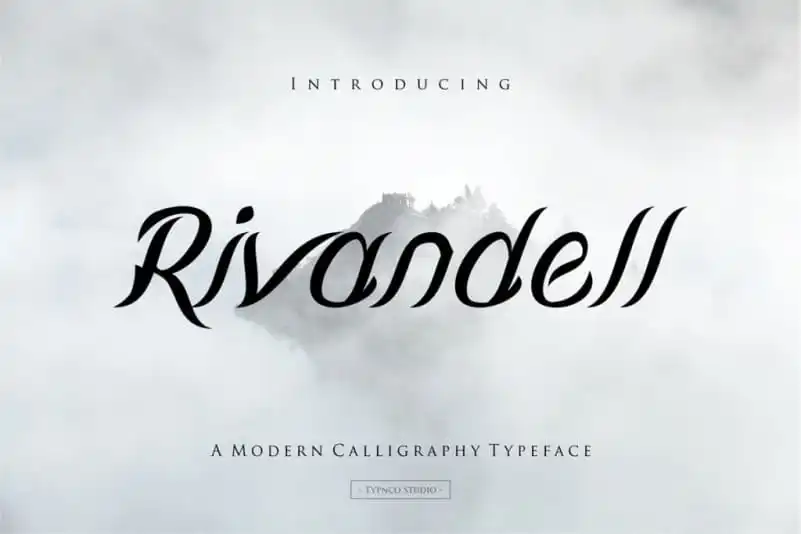
A Rivandell Script é uma nova fonte feita à mão com estilo calligrafico que se destaca no mercado das letras digitais. Esta fonte perfeita para postais de casamento traz um toque moderno às antigas grifes reais e ficcionais, mantendo-se fiel ao seu aspecto elegante e sofisticado. Rivandell é uma tipografia cursiva ideal para diversos projetos, desde convites de casamento até capas de livros ou pequenos ditames. A fonte foi criada por Typnco Studio e oferece um look autêntico e impecável que se destaca em ambos os ambientes impressos e digitais. Suas linhas fluidas e detalhes meticulosamente cuidados fazem da Rivandell Script uma escolha perfeita para quem deseja criar designs com uma forte presença visual, capazes de expressar elegância e elegância ao mesmo tempo. Composta por um conjunto de caracteres que inclui acentos diacríticos e simbolos, a fonte é versátil o suficiente para adaptar-se em diferentes formatos e aplicativos. Caso seja seu objetivo apresentar uma mensagem elegante e memorável, Rivandell Script pode ser uma escolha estratégica para sua próxima criação gráfica.